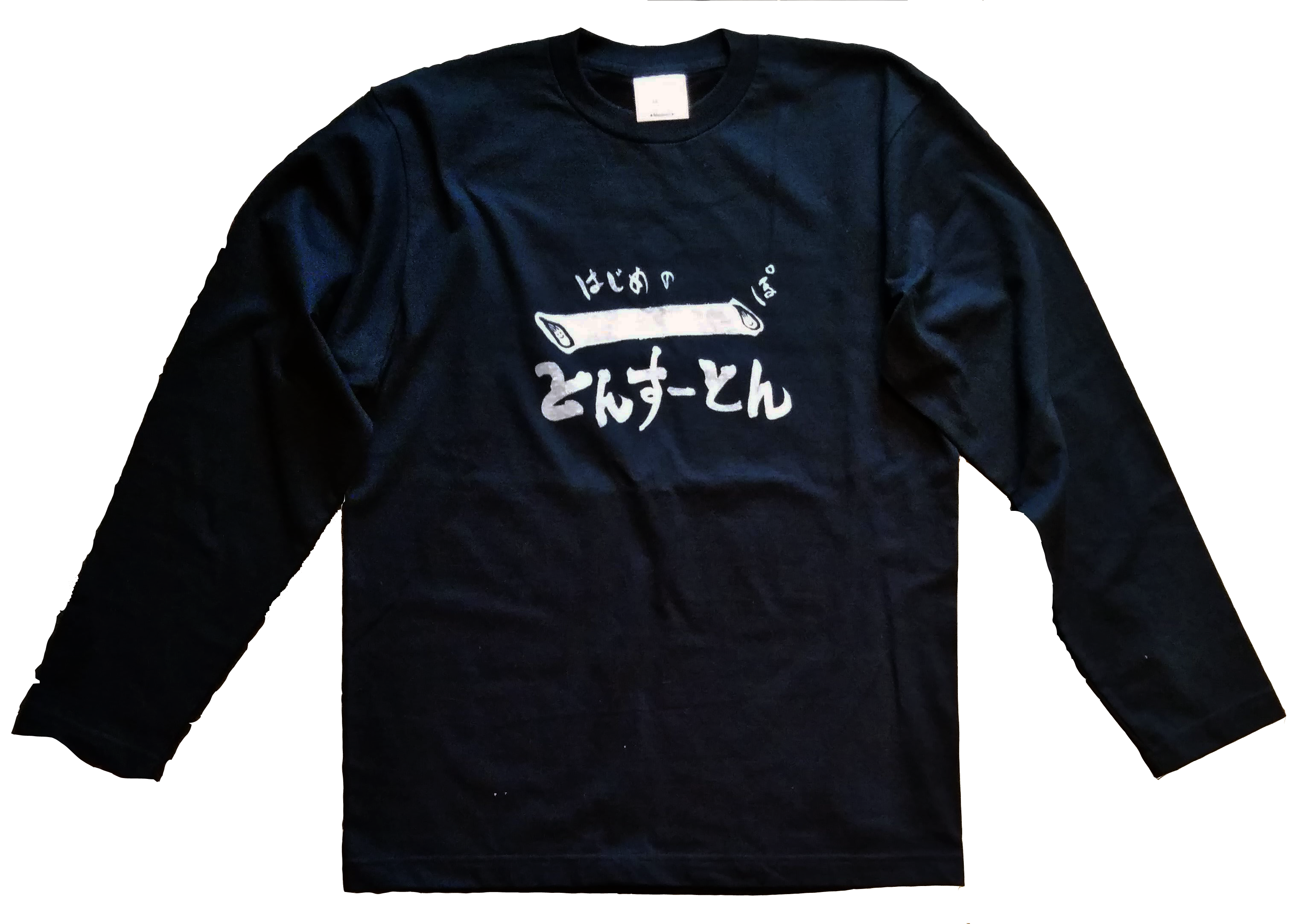
「とんすーとん」とは文字の基本。
筆で書くときはもちろん、
どのような筆記具でも「とんすーとん」がしっかりできている文字は美しい。
とん:始筆(はじまり)
すー:送筆(とちゅう)
とん:終筆(おわり)
どんな画でも、
しっかりはじまり、つながり、おさまる。
これを意識することで
文字(言葉)に流れやリズムが生まれる。
日本語は書く文化だから
言葉の基本とも言える。
はじめの一歩は
とんすーとんから。
やってみてね。
着てみてね。
そして、けんかしていてもあっという間に仲直り!
なぜなら「とんすーとん」と指でなぞり書きしてあげるのだ。
コミュニケーションを楽しみながら
字の練習ができる
なんというスグレモノ( ;∀;)
着るだけで字が美しくなるてぃーしゃつ**